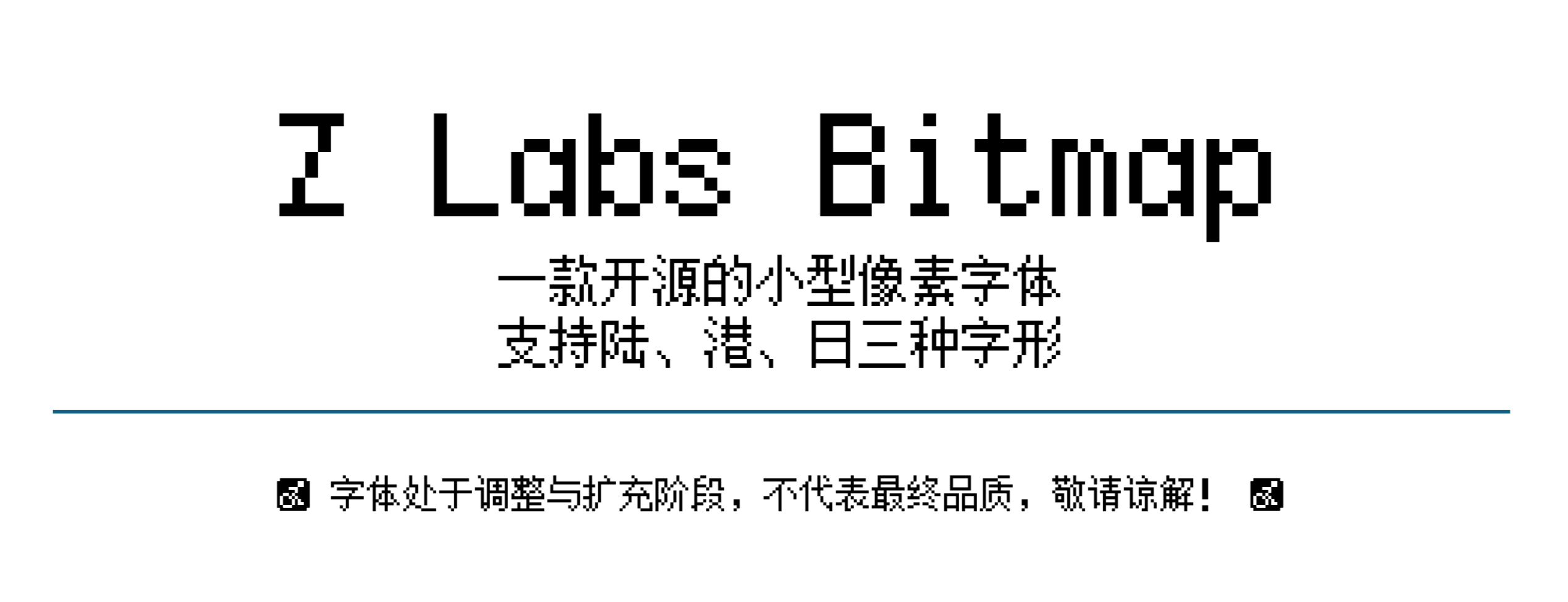
「Z Labs Bitmap」是一款小型化像素字体,具有中国大陆、中国香港、日本三种变体字形,西文字体按等宽规格设计。
字体目前已基本支持简体中文、繁体中文、日语。
字体覆盖范围
汉字
本字体不同版本变体的汉字支持情况不同。下面列出了每个版本变体的制作计划与具体支持情况。
中国大陆变体字形(CN)
✅ GB/T 2312 (6763 / 6763)
✅ 《通用规范汉字表》(8105 / 8105)
✅ Big5 常用汉字表(5401 / 5401)
✅《常用国字标准字体表》(4808 / 4808)
✅ GB/T 12345(6866 / 6866)
✅《通用规范汉字表》附件 1:「规范字与繁体字、异体字对照表」中的繁体字列(2563 / 2563)
✅ JIS X 0208(6355 / 6355)
ℹ️ 共计支持汉字:12926
中国香港变体字形(HC)
✅《常用国字标准字体表》(4808 / 4808)
✅ Big5 常用汉字表(5401 / 5401)
✅ GB/T 12345(6866 / 6866)
✅《通用规范汉字表》附件 1:「规范字与繁体字、异体字对照表」中的繁体字列(2563 / 2563)
✅ JIS X 0208(6355 / 6355)
ℹ️ 共计支持汉字:9977
日本变体字形(JP)
✅ JIS X 0208(6355 / 6355)
ℹ️ 共计支持汉字:6364
⚠️ 鉴于日语对汉字需求较小,若无特殊情况,日标字形将不再制作新的汉字字符。